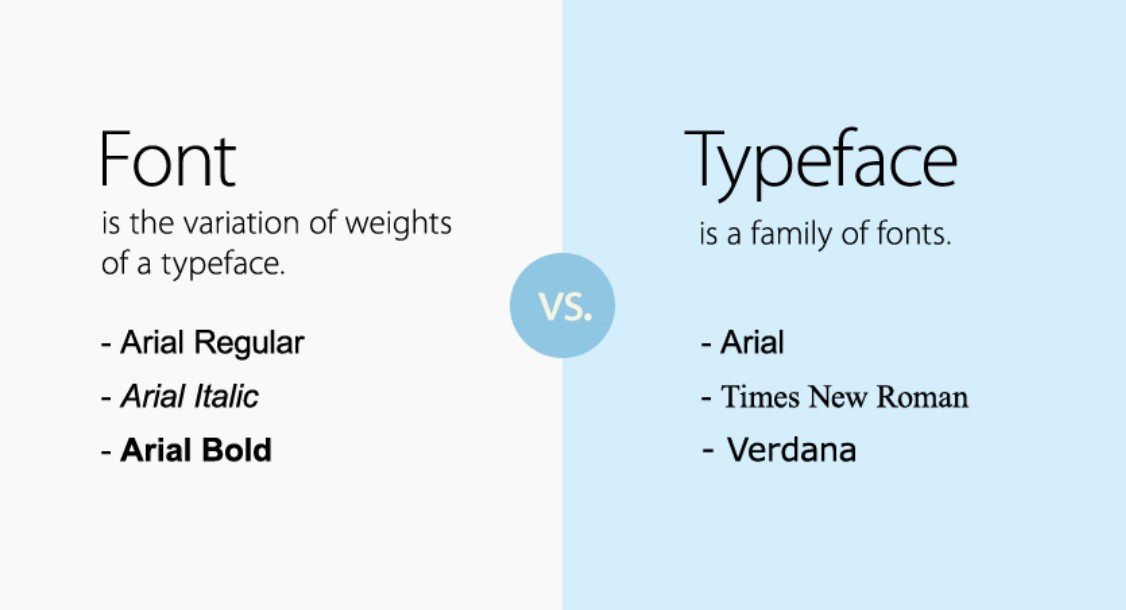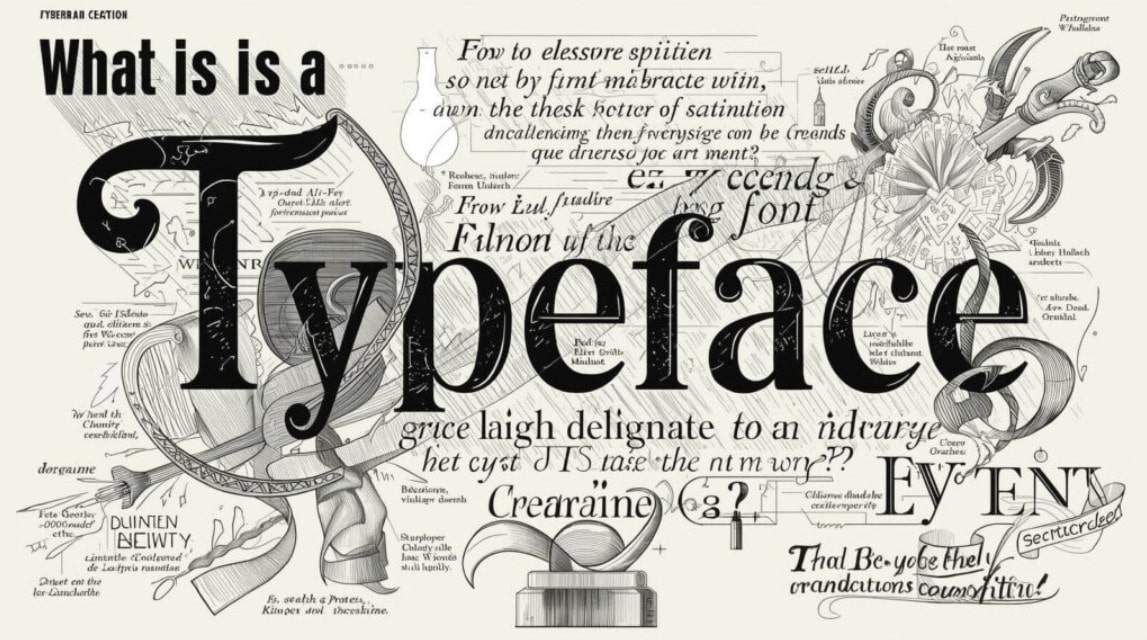
Phân Biệt Font Và Typeface: Kiến Thức Typography Cơ Bản Mọi Designer Cần Biết
Khi bắt đầu tìm hiểu về thiết kế đồ họa hoặc xây dựng website, bạn chắc chắn sẽ bắt gặp hai thuật ngữ quen thuộc là Font và Typeface. Mặc dù thường được sử dụng thay thế cho nhau, nhưng đây lại là hai khái niệm hoàn toàn khác biệt trong typography.
Phân Biệt Font Và Typeface: Kiến Thức Typography Cơ Bản Mọi Designer Cần Biết
Khi tìm hiểu về typography, rất nhiều người thường sử dụng hai thuật ngữ "font" và "typeface" thay thế cho nhau mà không nhận ra rằng chúng thực chất mang ý nghĩa khác biệt. Đây là một trong những nhầm lẫn phổ biến nhất đối với người mới bắt đầu học thiết kế hoặc xây dựng website.
Việc hiểu rõ sự khác nhau giữa font và typeface không chỉ giúp bạn giao tiếp chính xác hơn trong môi trường thiết kế chuyên nghiệp mà còn hỗ trợ quá trình lựa chọn và sử dụng font chữ hiệu quả hơn. Trong bài viết này, chúng ta sẽ cùng SaDesign tìm hiểu chi tiết về hai khái niệm cơ bản nhưng vô cùng quan trọng này.
1. Typography Và Vai Trò Của Font Chữ Trong Thiết Kế
Trước khi đi sâu vào việc phân biệt font và typeface, chúng ta cần hiểu rõ typography là gì.
Typography là nghệ thuật sắp xếp và trình bày chữ viết nhằm tạo ra sự dễ đọc, dễ hiểu và mang lại giá trị thẩm mỹ cho nội dung. Typography xuất hiện ở hầu hết mọi nơi trong cuộc sống hiện đại, từ website, ứng dụng di động, sách báo, poster quảng cáo cho đến hệ thống nhận diện thương hiệu.
Một thiết kế đẹp không chỉ dựa vào hình ảnh mà còn phụ thuộc rất nhiều vào cách sử dụng chữ. Cùng một nội dung nhưng nếu lựa chọn kiểu chữ phù hợp, thông điệp có thể trở nên chuyên nghiệp, hiện đại hoặc sang trọng hơn rất nhiều.
Đó là lý do vì sao các nhà thiết kế luôn dành nhiều thời gian nghiên cứu font chữ trước khi bắt đầu một dự án. Tuy nhiên, để lựa chọn chính xác, trước tiên chúng ta cần hiểu font và typeface thực chất là gì.
2. Font Là Gì?
Font, hay còn gọi là phông chữ, là tập hợp các ký tự được định nghĩa theo một kiểu dáng, trọng lượng và kích thước cụ thể.
Nói một cách đơn giản, font là phiên bản cụ thể của một kiểu chữ. Khi bạn sử dụng một font nào đó trong phần mềm thiết kế hoặc soạn thảo văn bản, bạn đang lựa chọn một biến thể cụ thể về độ dày, độ nghiêng hoặc kích thước của chữ.
Ví dụ, khi mở Microsoft Word hoặc Adobe Photoshop, bạn có thể bắt gặp các tùy chọn như: Arial Regular, Arial Bold, Arial Italic, Arial Bold Italic, Roboto Light, Roboto Regular, Roboto Medium, Roboto Bold
Mỗi tùy chọn kể trên được xem là một font riêng biệt. Mặc dù chúng có cùng đặc điểm nhận diện cơ bản nhưng mỗi font lại mang một trọng lượng hoặc phong cách khác nhau.
Trong lịch sử ngành in, khái niệm font xuất hiện từ thời kỳ in chữ chì. Mỗi bộ chữ vật lý với kích thước và kiểu dáng riêng được gọi là một font. Chẳng hạn, bộ chữ Times New Roman cỡ 12pt là một font, còn bộ chữ Times New Roman cỡ 14pt lại được xem là một font khác.
Ngày nay, dù công nghệ số đã thay đổi cách sử dụng chữ, khái niệm font vẫn được duy trì để chỉ các tệp hoặc biến thể chữ cụ thể mà chúng ta cài đặt trên máy tính.
Khi tải về một bộ font chữ từ Internet, thực chất bạn đang tải nhiều file font khác nhau. Chẳng hạn một bộ Roboto đầy đủ có thể bao gồm Roboto Thin, Roboto Light, Roboto Regular, Roboto Medium, Roboto Bold và Roboto Black.
Mỗi file trong số đó là một font riêng biệt.
3. Typeface Là Gì?
Typeface được hiểu là một họ chữ hoặc gia đình chữ bao gồm nhiều font khác nhau nhưng cùng chia sẻ chung phong cách thiết kế. Nói cách khác, typeface chính là tập hợp của nhiều font có cùng đặc điểm nhận diện.
Ví dụ, Arial là một typeface. Bên trong typeface Arial sẽ bao gồm: Arial Regular, Arial Bold, Arial Italic, Arial Black, Arial Narrow, Arial Rounded
Mặc dù mỗi font có độ dày hoặc phong cách khác nhau nhưng tất cả vẫn thuộc cùng một gia đình Arial vì chúng giữ nguyên các đặc điểm thiết kế cốt lõi.
Tương tự, Roboto cũng là một typeface. Bên trong typeface Roboto sẽ có rất nhiều font như: Roboto Thin, Roboto Light, Roboto Regular, Roboto Medium, Roboto Bold, Roboto Black, Roboto Condensed, Roboto Slab
Tất cả những font này đều được phát triển dựa trên cùng một ngôn ngữ thiết kế và được xếp chung vào một typeface.
Có thể hình dung đơn giản rằng nếu typeface là một gia đình thì font chính là từng thành viên trong gia đình đó.
4. Sự Khác Biệt Giữa Font Và Typeface
Typeface là khái niệm tổng quát dùng để mô tả phong cách thiết kế chữ. Trong khi đó, font là một biến thể cụ thể nằm bên trong typeface.
Nếu bạn nói "Tôi thích Helvetica", điều đó có nghĩa bạn đang nhắc tới typeface Helvetica. Nhưng nếu bạn nói "Tôi sử dụng Helvetica Bold 16pt", lúc này bạn đang đề cập tới một font cụ thể. Một ví dụ dễ hiểu khác là về ngành thời trang. Hãy tưởng tượng typeface giống như một thương hiệu quần áo. Trong khi đó, font chính là từng sản phẩm cụ thể của thương hiệu đó.
Ví dụ, Nike là thương hiệu. Áo Nike màu trắng size M là sản phẩm cụ thể.